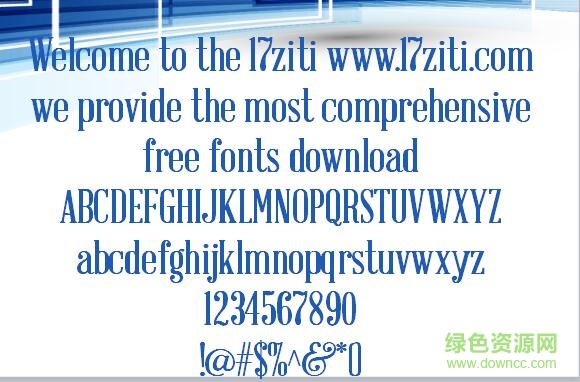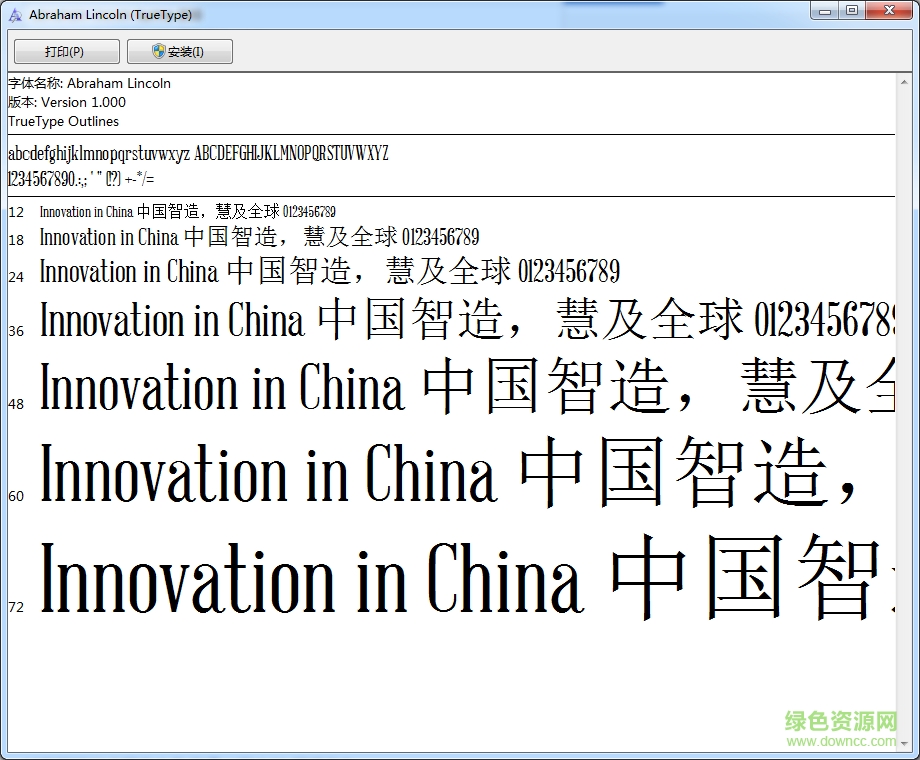
abrahamlincoln字體
abrahamlincoln是一款簡(jiǎn)單實(shí)用的電腦字體軟件,字體簡(jiǎn)潔端正大方,線條流暢極具美感,使用簡(jiǎn)單時(shí)刻彰顯個(gè)人魅力??靵?lái)綠色資源網(wǎng)下載體驗(yàn)吧!
abrahamlincoln字體介紹
abrahamlincoln字體是一款風(fēng)格非常鮮明的中文字體,端正、橫豎整齊,字體又有一點(diǎn)分叉的小心機(jī)設(shè)計(jì),非常時(shí)尚。